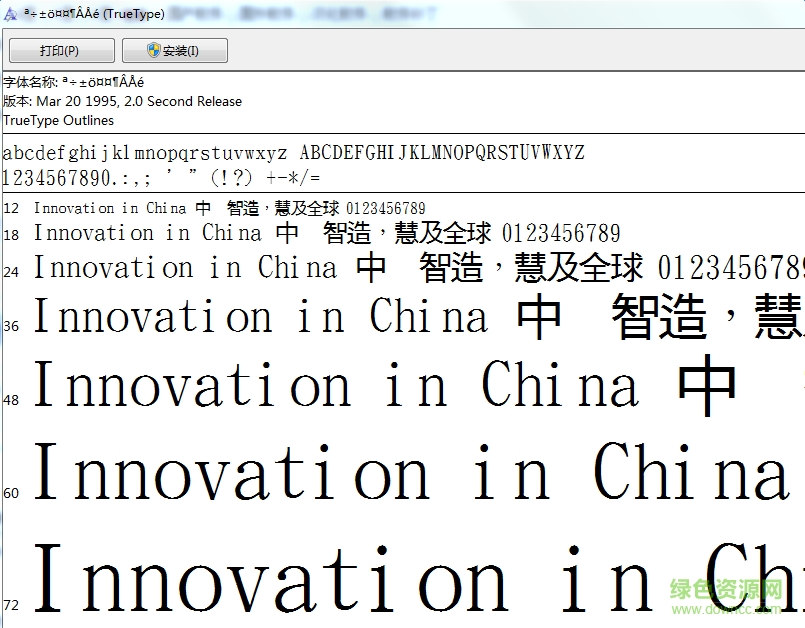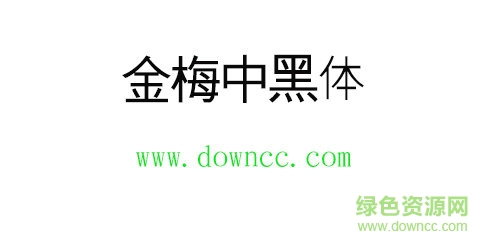
金梅中黑體字體是一款金梅字體中文黑體字體,包含簡體和繁體字體,十分好用,您還在等什么?官方打造,非常好用,字體整潔排序,而且設(shè)計(jì)畫面也非常具有個性,也能讓你文字設(shè)計(jì)更加突出,容易被發(fā)現(xiàn)哦,感興趣的就來本站下載使用吧!
1. 更優(yōu)美而現(xiàn)代的字形設(shè)計(jì)。
2. 單獨(dú)設(shè)計(jì)的粗體。
3. 更清晰的小號字顯示。
3. 顯示品質(zhì)優(yōu)異的斜體。